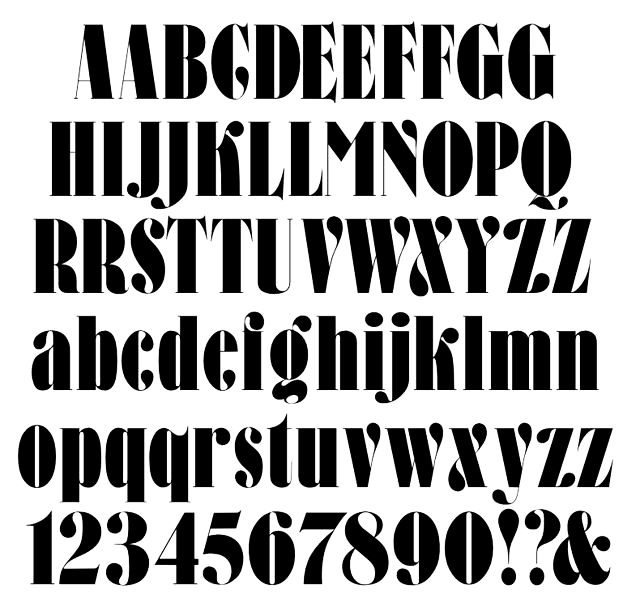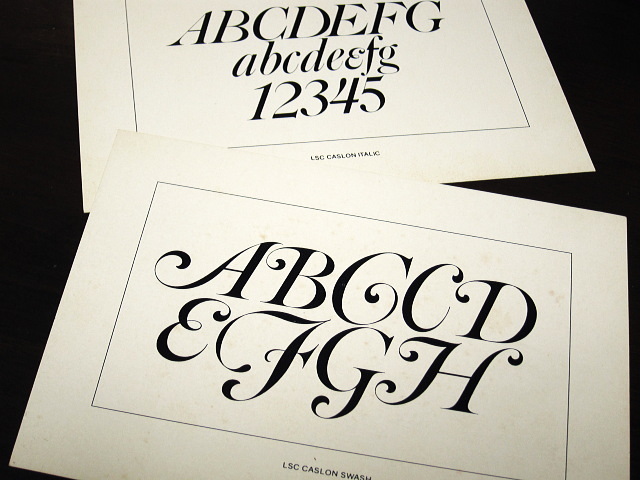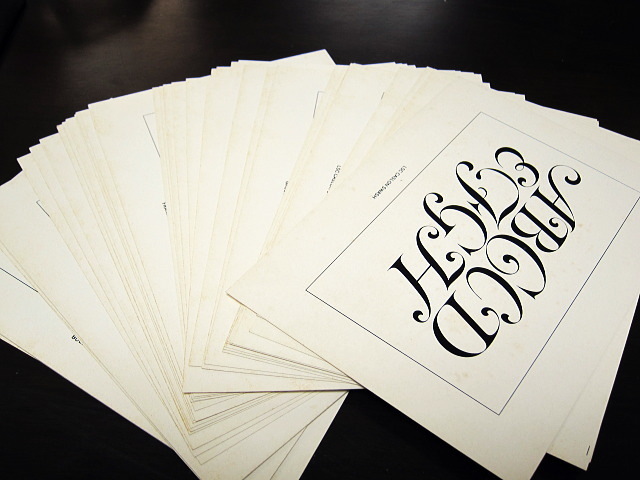
オリジナルフォント Garamond DF |
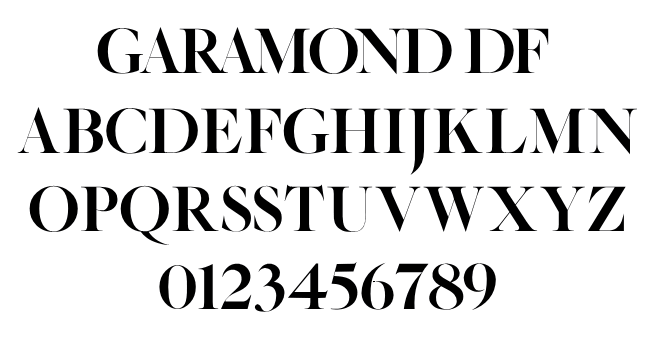
去年からコツコツとつくっていたオリジナルフォント「Garamond DF」の大文字と数字がほぼ完成。
不変的な骨格をより強調させるため、極端なコントラストを施しました。
このあたりは、ずっと研究しているトム・カーネイズ(Tom Carnase)の影響です。
ここに掲載された
Didi の原型となったと思われる書体を見てください。
彼のレタリングは本当に極端なんです!
特に「S」は納得するカーブが引けるまで、何度も何度も修正。
数字に関しては、SIMONE
INC. 率いるムラカミカイエさんからアドバイスをいただきました。
あとは小文字と記号をつくって、年内を目途に完成予定。
是非、お持ちの「Garamond」と比較してみてください。 |
Garamond DF by Daylight Fonts in 2010 |
ファッション写真×書体 サエグサアヤさんとのコラボ |
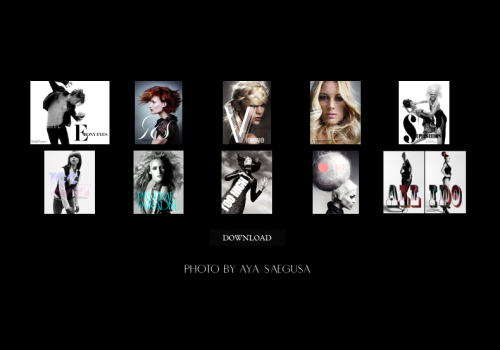
ファッション写真家サエグサアヤさんとのプロジェクト。
フォント化されていない書体を復刻したリバイバルフォントと
オリジナルフォントをメインに使用した実験的タイポグラフィー作品です。
きのう、サエグさんよりはじめてメッセージをいただき、
彼女のブログを見ると、文字を乗せたい素晴らしい写真ばかり!
その趣旨を伝えると、トントン拍子に使用許可がいただけたので、
さっそくサエグさんのブログから写真を10枚ピックアップし、 1時間ほどで完成。
やっぱりいい写真だと、サクサク作業が進みます。
文字は、たまたまスティーヴィー・ワンダーの曲を聴いていたので、彼の曲名から。
これでオリジナル・復刻フォントの実験ができると思うと、なんだか水を得た魚のような気分で爽快!
まだテスト段階ですが、チェックしてみてください。
贔屓になっているパージナさんより、LSC社の書体カタログが届いた。
LSC社(Lubalin, Smith, Carnase Inc.)とは、ハーブ・ルバーリン、アーニー・スミス、トム・カーネイズによって
1969年に設立された会社で、主にオリジナル書体の供給がメインだったよう。
「Avant
Garde Gothic」や「Serif
Gothic」、「Lubalin
Graph」など、
現在でもよく使われている名書体がここからITC社へ供給された。
同カタログは44枚の書体シート、つまり44書体を収録。
古い本なので、本当はもっとシートが入っていたかも知れない。
「LSC Manhattan」(ITC
Manhattan)が「LSC Broadway」、
「LSC Book」(ITC Book)が「LSC Hess」という名前で掲載されていて、その創成期をうかがい知ることができる。
以上の内容から、このカタログはITCが設立される前の1969年か1970年頃のものと推測。
一番の収穫は、この一年ずっと探し求めていた幻の書体「LSC Caslon Swash」が収録されていたこと。
この書体は「LSC Caslon Italic」同様、正式にリリースされたかさえ不明だ。 |
リバイバルフォント Caslon Headline |
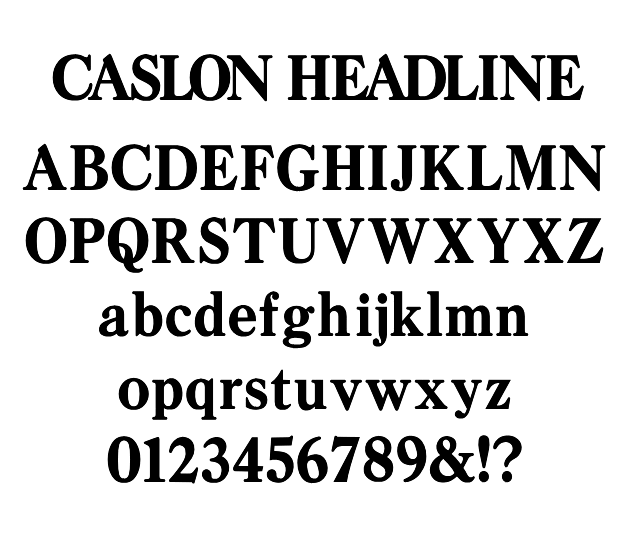
レア書体「Caslon Headline」を復刻してみた。
リリースはおそらく1970年で、デザインはハーブ・ルバーリンとトム・カーネイズ。
ヘッドラインというだけあって、わりとオーソドックスなデザインですね。
ウエイトはこれのみ。
特徴は 6 や 9 が傾いていて、J と j の処理もいい感じ。
これで公式的に LSC 社(Lubalin, Smith, Carnase)からリリースされた書体はひととおり揃ったので、
あとは、「Caslon 223」と「LSC Book」の各ウエイトを復刻するのと、
謎に包まれた「Caslon Swash」の資料を入手するだけ。 |
Caslon Headline by Herb Lubalin, Tom Carnase fot LSC / ITC in 1970 |
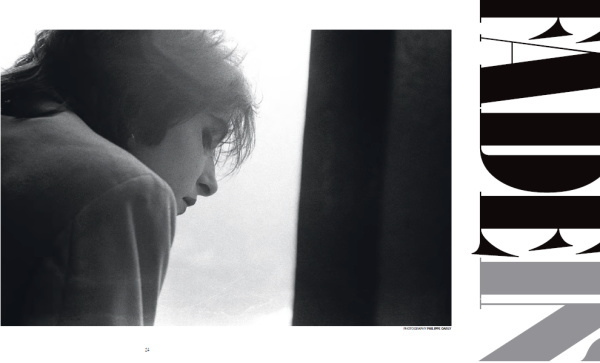
アメリカの音楽雑誌『FADER』
Issue 67 に僕がデザインしたオリジナルフォント「Bernhard Neo」が掲載されました。
15, 16-20, 67ページ
なんかこうして自分がつくったものが印刷されるって、うれしいですね。
この2年近く、書体に没頭した甲斐がありました。
さて、掲載までの経緯です。
以前からコツコツとつくっていた「Bernhard Neo」のコンセプトデザインを
NYのグラフィックデザイナー
Justin
Thomas Kay 氏に見せると、
「新しく携わる雑誌で使いたいから至急送ってくれ!」とメールが来たので、慌てて制作。
ベースは「Bernhard」という1912年にリリースされた大好きな書体で、
これをモダンにアレンジできないかなぁとスケッチしていたわけです。
参考にしたのは、ルバーリンとカーネイズによる「Fat
Face」。
なんといっても、このふっきれ感が大好きで、
ローマンにカーネイズ特有のカリグラフィーのテイストを盛り込んだ、個性的な書体を目指しました。
極度のコントラストを施したおがけで、より骨格が強調されていると思います。
急いで仕上げたので、もう少しいじる予定。
ちなみにジャスティンは『FADER』誌のクリエイティブ・ディレクターで、
去年末にルバーリンの母校クーパーユニオン大学で開催された「Lubalin
Now」のロゴを手掛けた人物。
レア書体好きです。
Bernhard Neo by Daylight Fonts in 2010 |